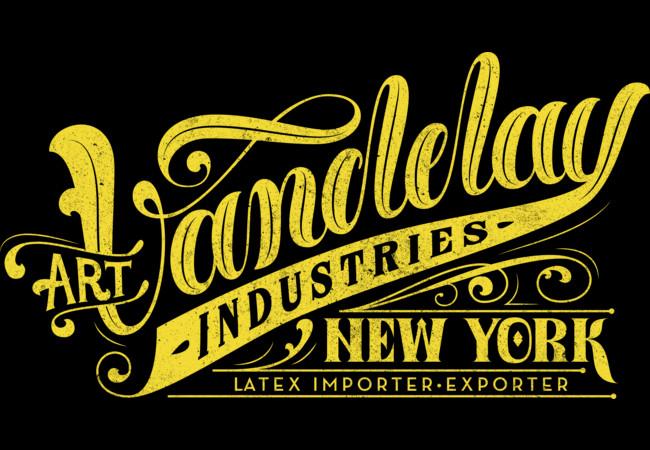
Was ist das für eine Schrift? (oder ähnliche)
ich suche schon Tagelang nach dieser Schrift (Siehe Bild) wisst ihr vielleicht welche Schriftart es sein könnte oder kennt Alternativen?
So etwas nennt sich "Lettering" und wird nicht aus einer Satzschrift gesetzt, sondern spontan und frei geschrieben oder gezeichnet / gemalt. Dasist praktisch eine Schildermaler-Tradition, und in den Typo-Videos hier, gibt es ein par schöne Beispiele dieser Kunst, die sich zwar an typoische Stile der jeweiligen Zeit anlehnt, aber letztlich jeden Schriftzug frei gestaltet.
ich denke auch das es handmade ist, mit etwas geschick kann man aber auch einen font so verformen, dass es ähnliche ergebnisse gibt. kommt natürlich auf die schrift drauf an.
eventuell helfen ja diese fonts weiter:
https://www.myfonts.com/fonts/sudtipos/festival-script-pro
https://www.myfonts.com/fonts/letraset/greyton-script
https://www.myfonts.com/fonts/dstype/aparo
https://www.myfonts.com/fonts/resistenza/superb
https://www.myfonts.com/fonts/sudtipos/fan-script